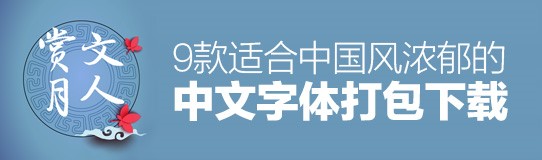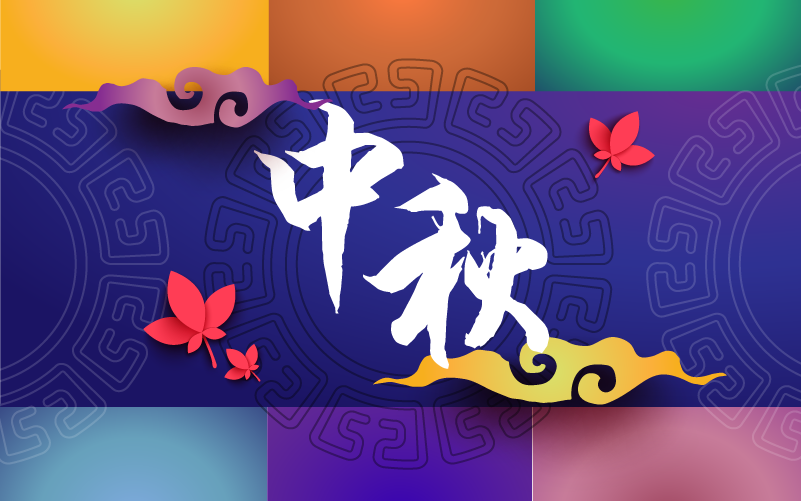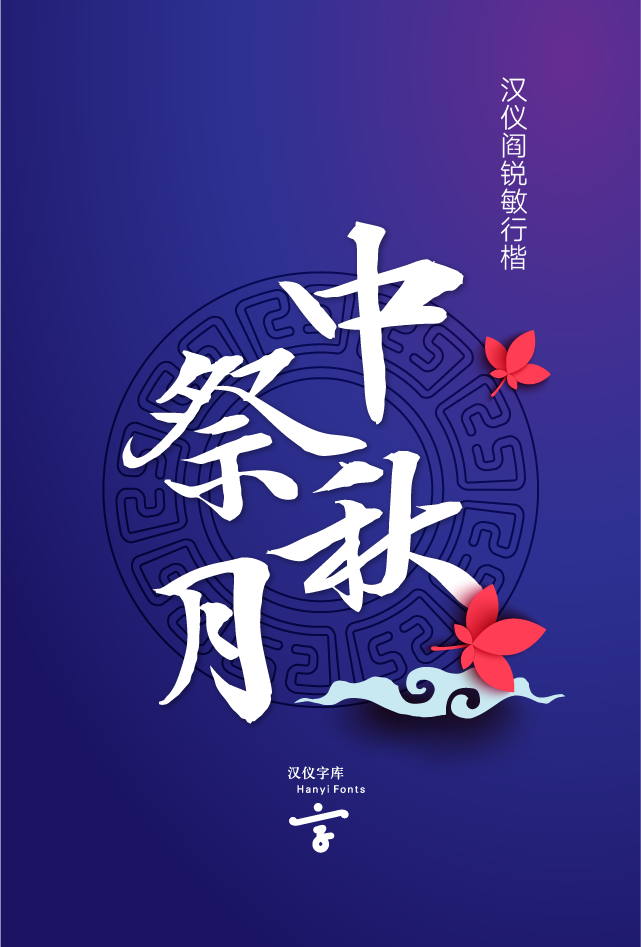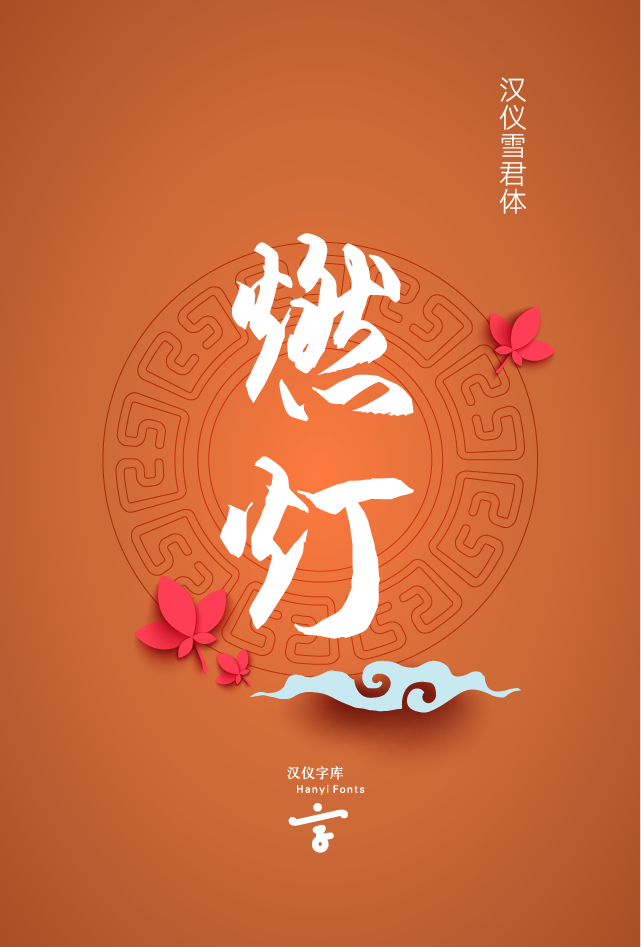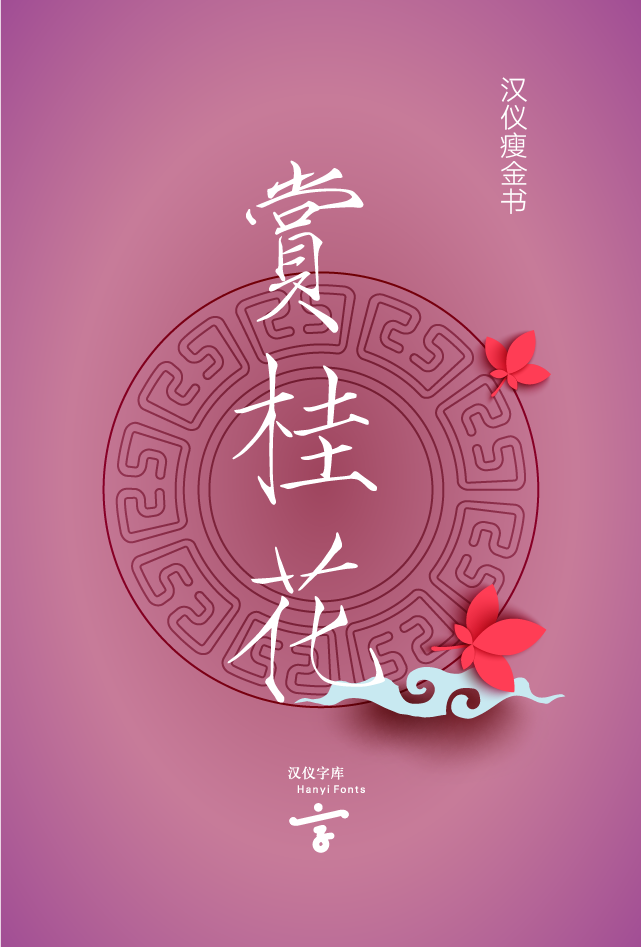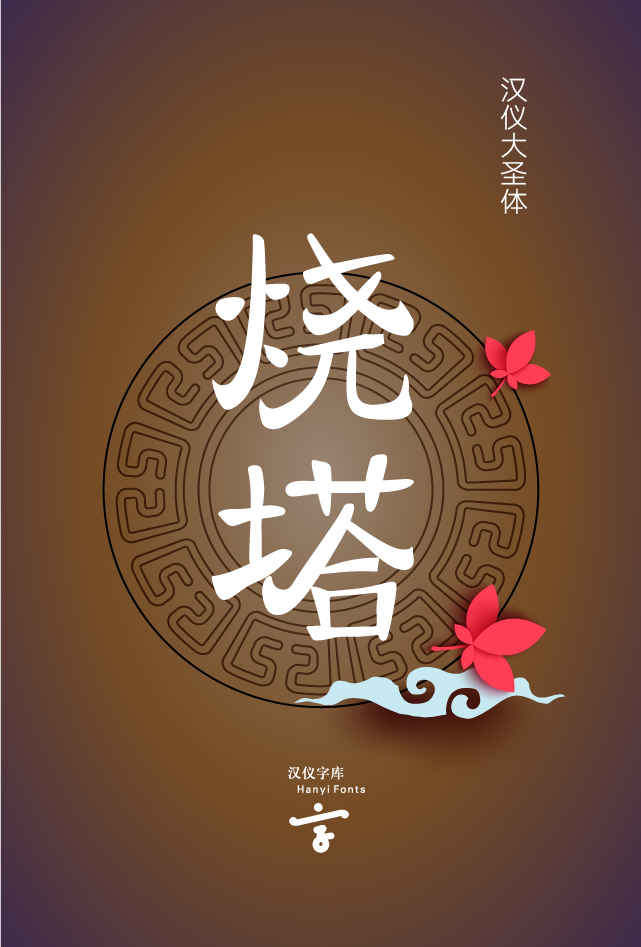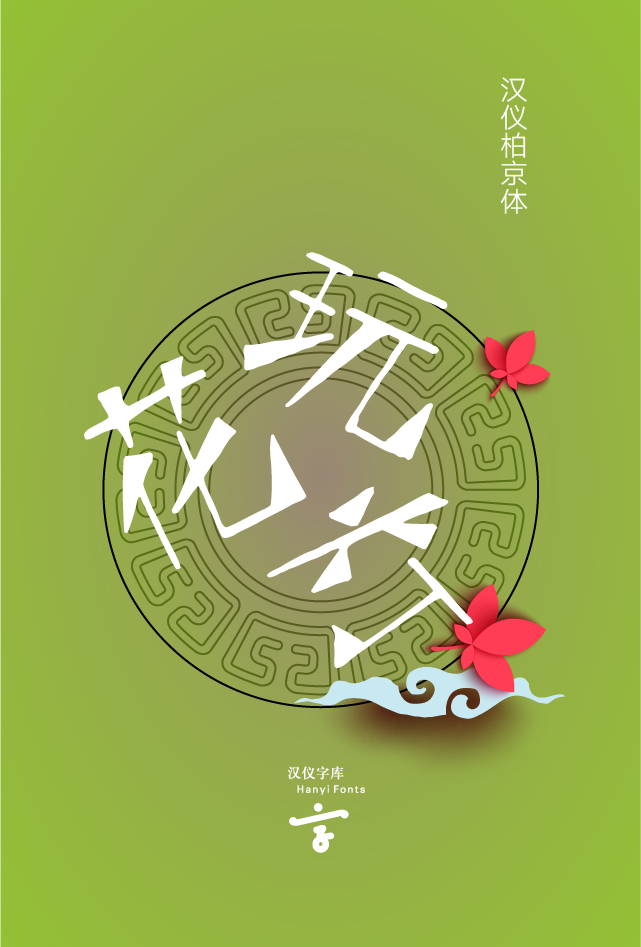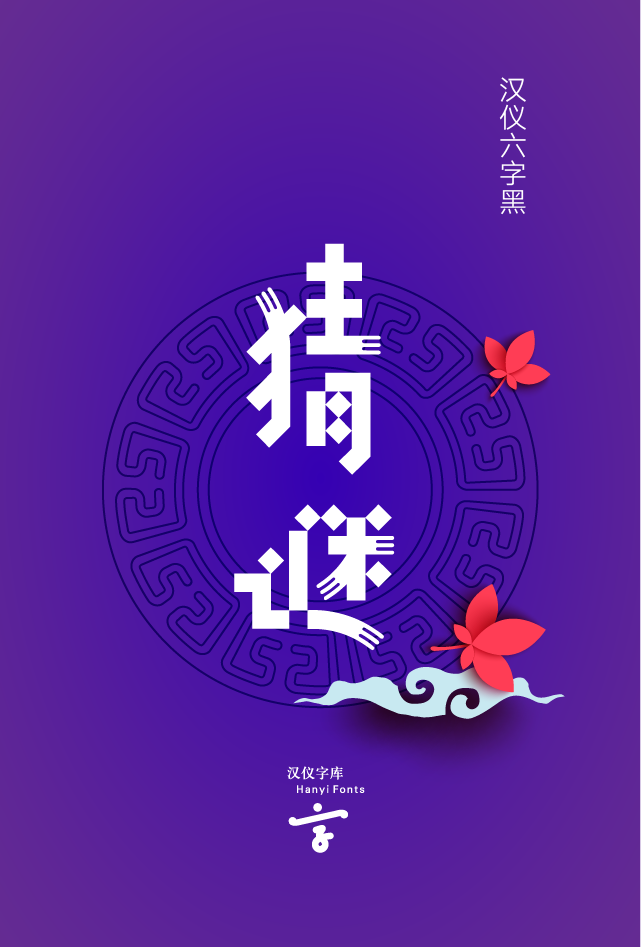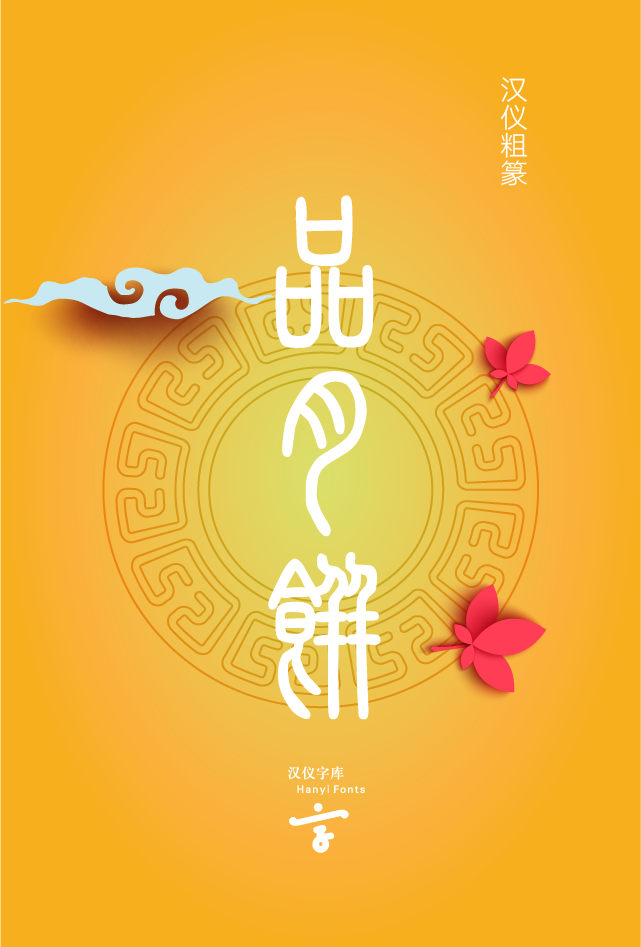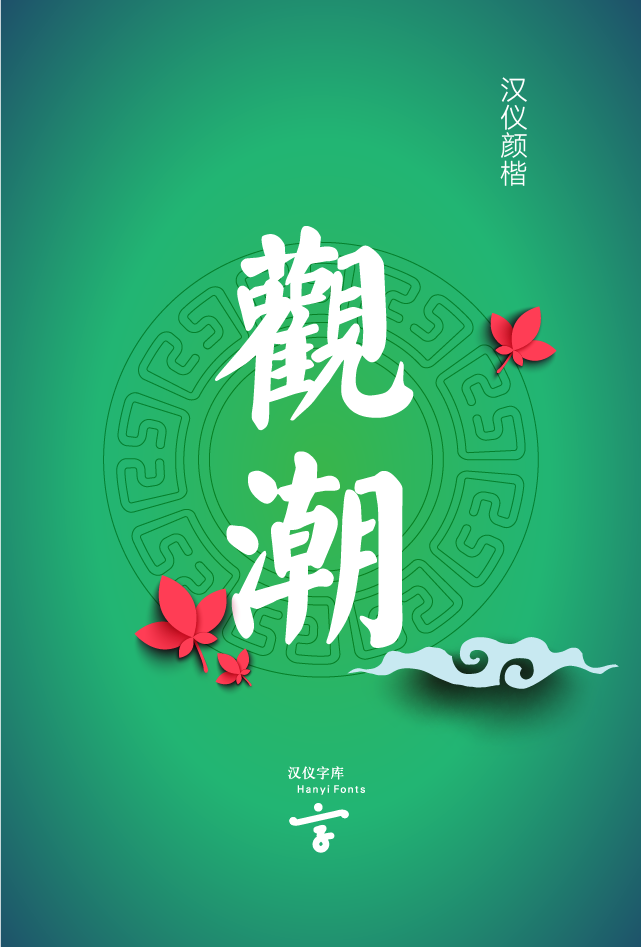
中秋佳节已经过去一段时间,想必设计师都忙着春节 Banner 海报等相关设计了吧,今天@汉仪字库 为大家整理了一组在中秋节用到过的字体,适特别适合中国风场景的中文字体素材包,相信对大家设计春节海报也会有帮助!包含9款中文字体,已经打包,最近要素材的同学赶紧来收!
中秋祭月
字体:汉仪闫瑞敏行楷
燃灯
字体:汉仪雪君体
赏桂花
字体:汉仪瘦金书
烧塔
字体:汉仪大圣体
玩花灯
字体:汉仪柏京体
猜谜
字体:汉仪六字黑
品月饼
字体:汉仪粗篆
观潮
字体:汉仪颜楷
文人赏月
字体:汉仪国强行书